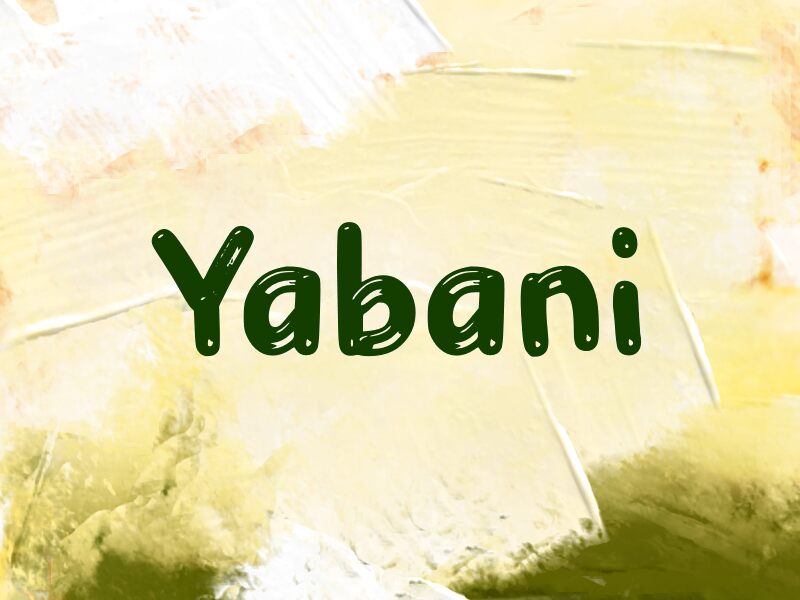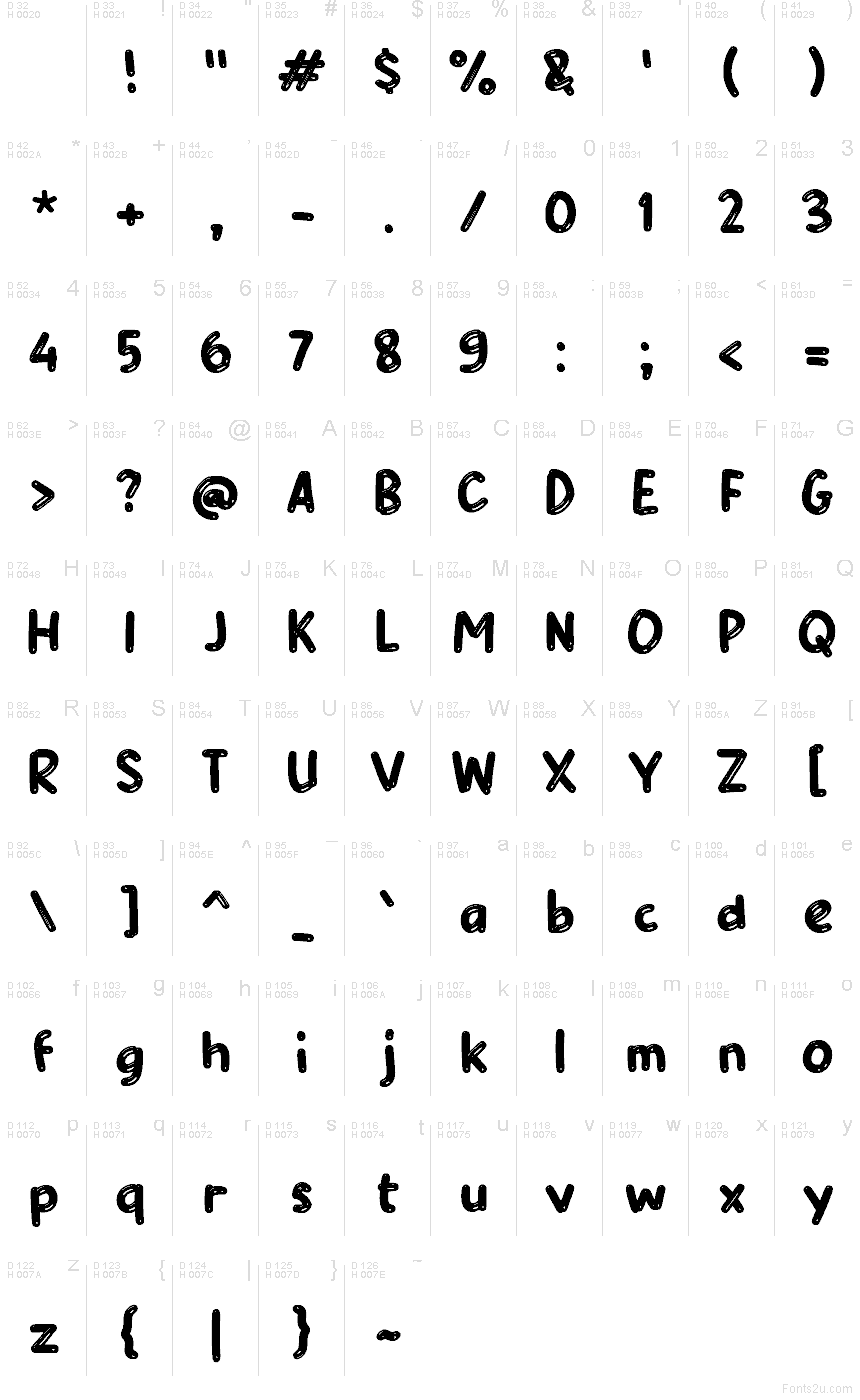
Yabani
Yabani, da Wep, é uma fonte display gratuita no estilo cartoon. Suas letras arredondadas e infladas parecem desenhadas com um marcador grosso, marcadas por riscos brancos rápidos. Esse preenchimento arranhado dá à fonte uma textura viva e brilhante, fazendo com que as silhuetas suaves pareçam mais como títulos de quadrinhos feitos à mão do que apenas bolhas limpas.
A fonte é ideal para pôsteres infantis, cabeçalhos de estilo cômico, embalagens de snacks, adesivos divertidos e miniaturas do YouTube, onde uma estética artesanal ajuda as palavras a ganharem movimento. Títulos curtos são os que mais se beneficiam, especialmente quando você busca formas grandes e redondas com uma textura interna rugosa que evita que a tipografia pareça genérica ou lisa demais.